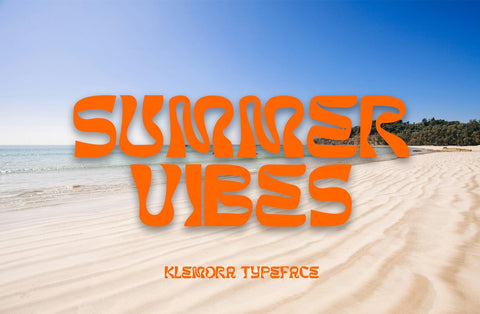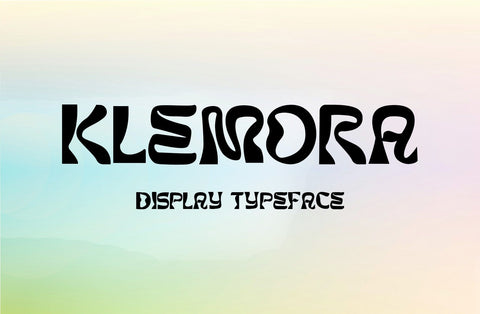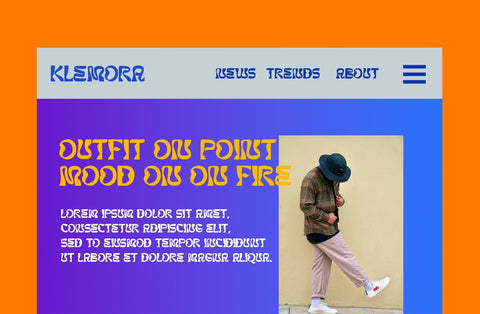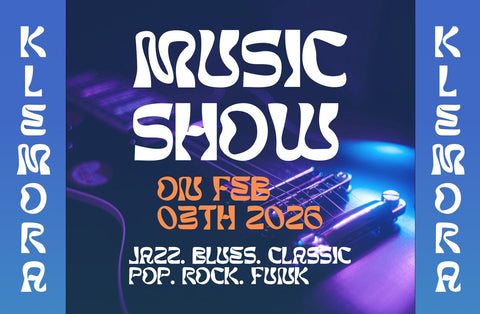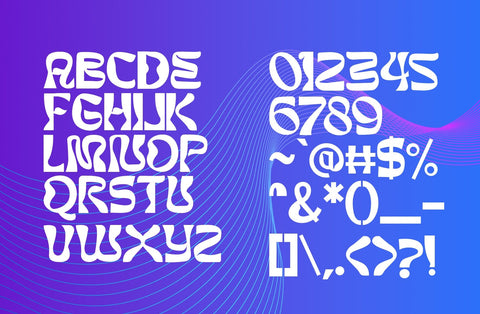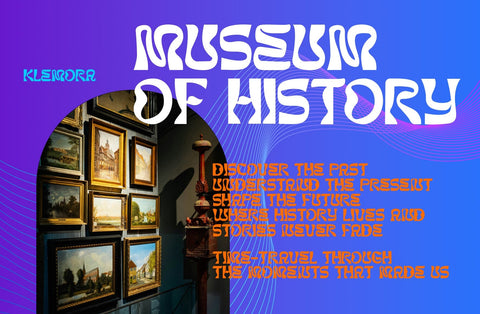
Klemora - Display Typeface
Memperkenalkan Klemora!! KLEMORA adalah font tampilan yang berani dan modern. Font ini modern dan klasik dengan tampilan yang unik dan berkelas. Sempurna jika Anda membutuhkan sedikit kesenangan dalam proyek Anda. Sempurna untuk proyek editorial, desain logo, font web, merek pakaian, kemasan produk, tajuk majalah, atau sekadar sebagai hamparan teks bergaya pada gambar latar belakang apa pun.